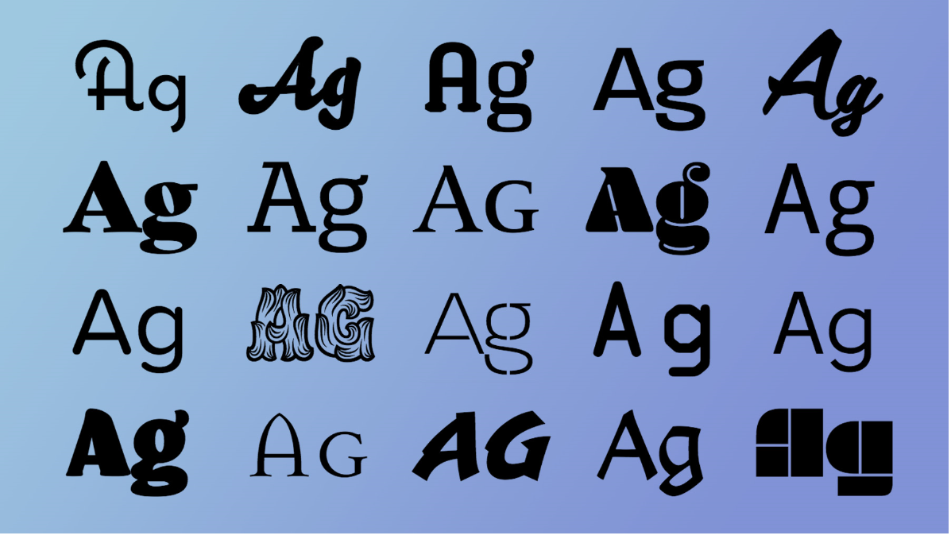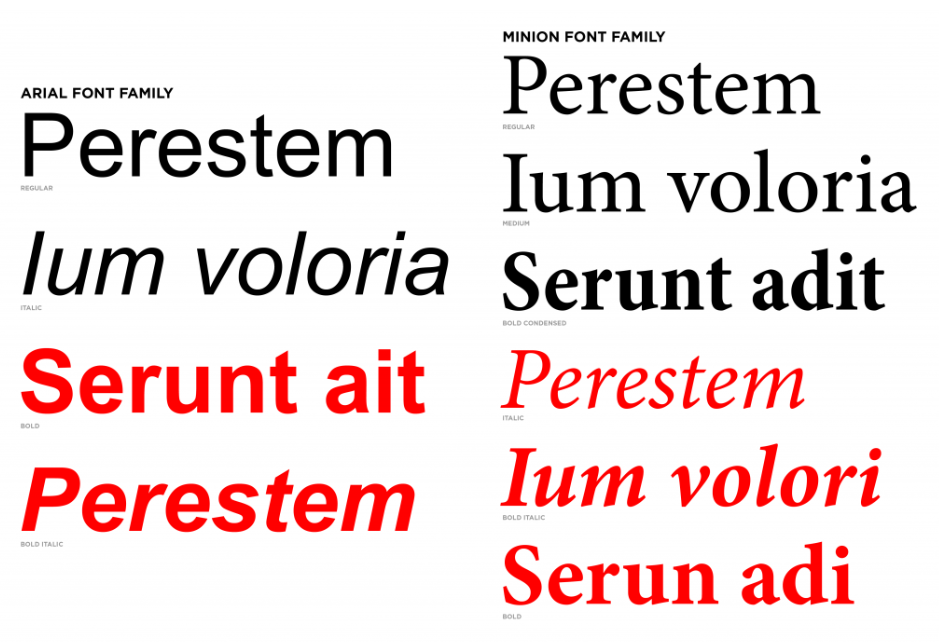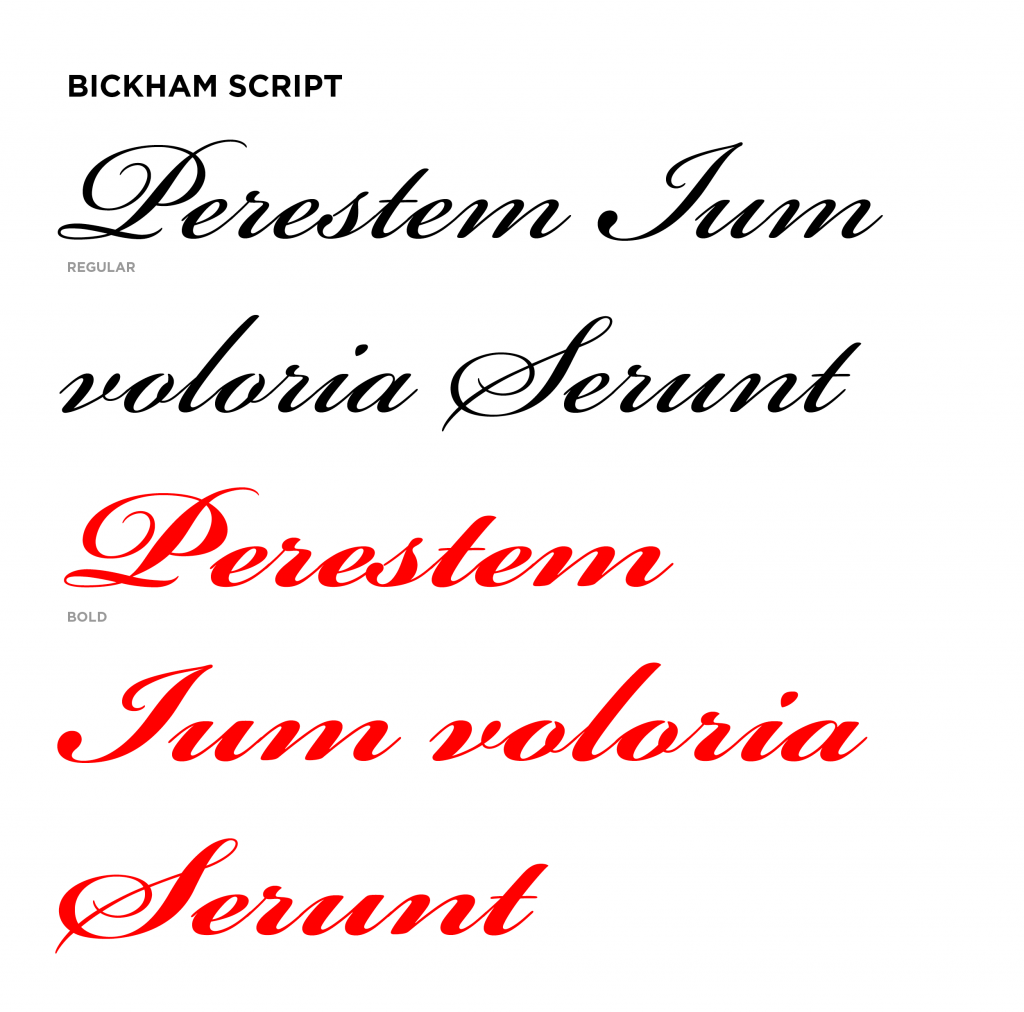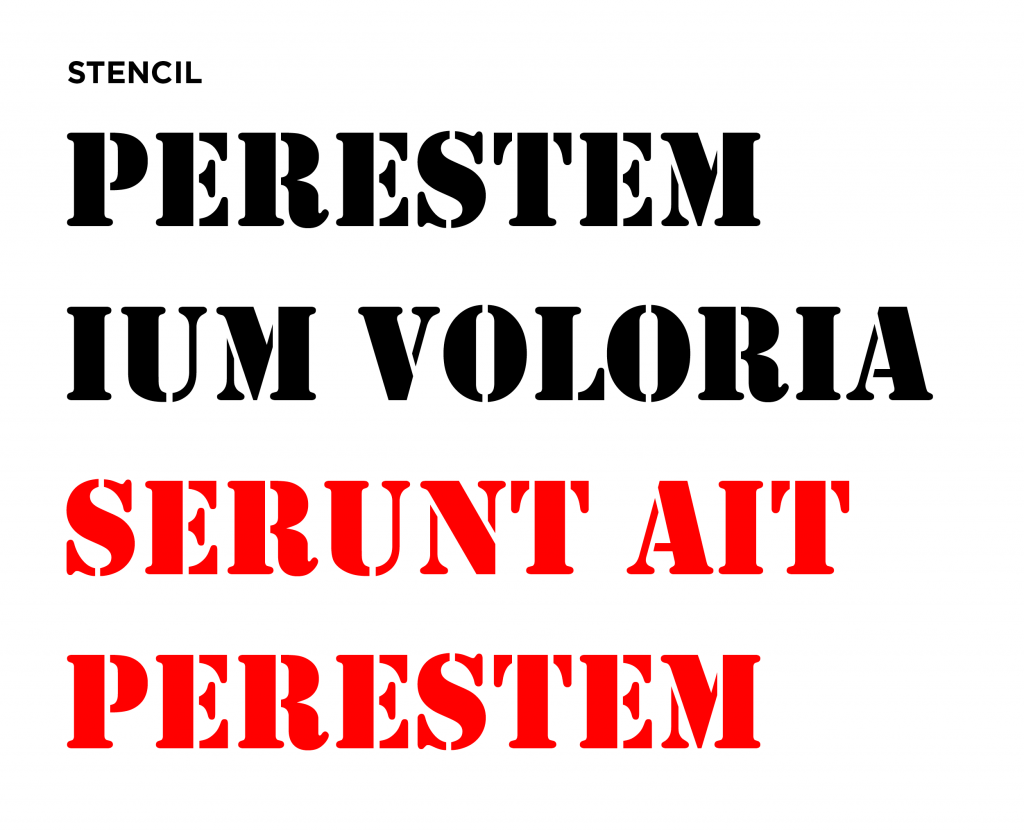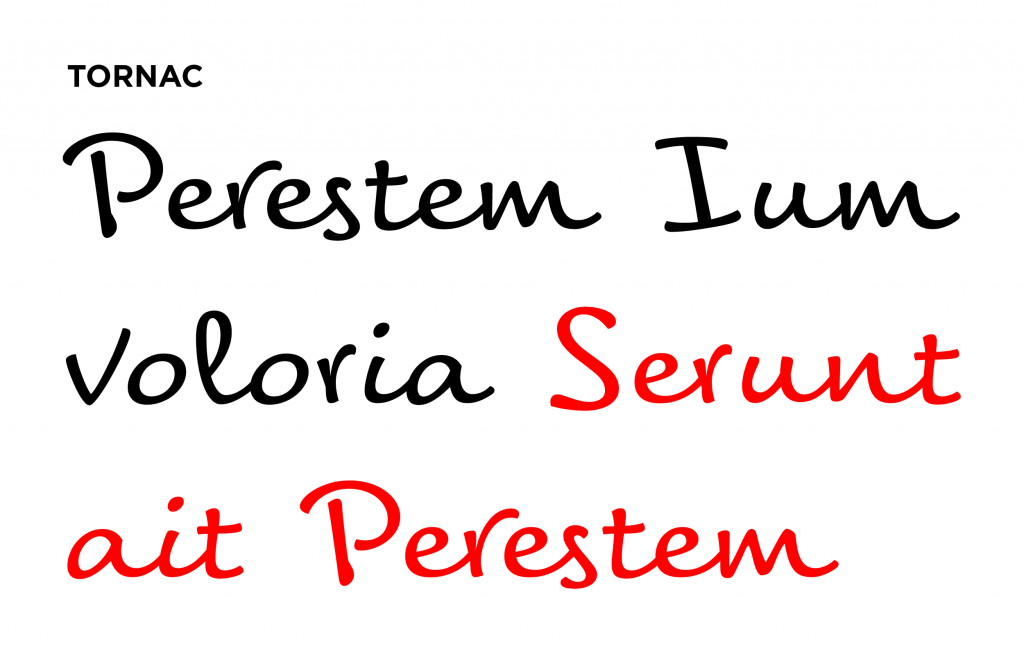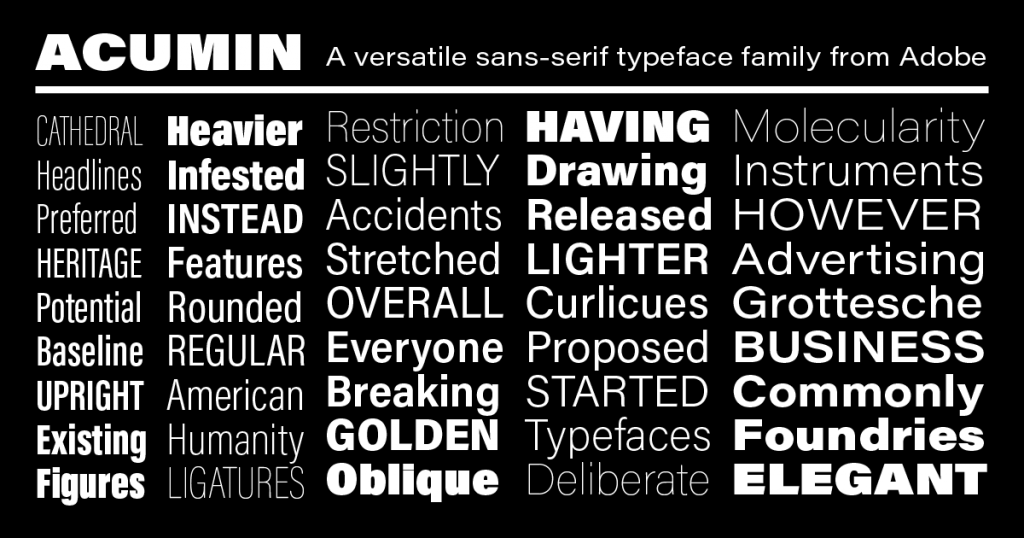
글꼴의 기능과 디자인에 적합한 글꼴 선택 방법
디자이너는 여러 종류의 디자인 의뢰를 받습니다. 예컨대 회사 세미나를 홍보하는 전단이나 친구의 결혼식 청첩장까지 다양합니다. 디자이너는 프로젝트가 최종적으로 어떻게 보여져야 하는지 알고 있습니다. 어떤 느낌을 전달해야 하는지도 알지만, 결과물은 어딘지 모르게 미흡합니다.
이와 비슷한 경험이 있다면 글꼴에 주목할 필요가 있습니다.
| 글꼴의 정의
워드 프로세서를 사용해 본 사람이라면 “글꼴”에 대한 기본적인 이해가 있을 것입니다. 그러나 의미 전달 측면에서 글꼴이 중요한 역할을 하는 디자인 프로젝트를 수행하는 경우 활자, 서체 및 글꼴의 차이점을 명확하게 파악하고 있어야 합니다.
• 활자는 현재 시각적인 문자를 통칭하는 일반적인 용어이지만, 본래는 글자를 만드는 데 사용된 나무 또는 금속 조각을 일컫는 말이었습니다.
• 타이포그래피는 인쇄된 텍스트의 스타일과 모양을 가리키는 디자인 용어입니다. 디자이너는 텍스트를 시각적으로 디자인하고 배열함으로써 타이포그래피를 전문적으로 다룰 수 있습니다.
• 서체(또는 글꼴 모음)는 글자 및 기호가 서로 비슷한 특징을 가지도록 디자인된 문자입니다. 예를 들어 타임즈(Times), 에어리얼(Arial) 및 미니언(Minion)은 모두 서체에 해당합니다.
• 글꼴은 서체의 특정 스타일을 가리킵니다. 에어리얼 블랙(Arial Black)은 에어리얼 서체 중 한 글꼴입니다. 미니언 프로 이탤릭체(Minion Pro Italic)는 미니언 글꼴 모음에 포함되어 있는 글꼴입니다.
“글꼴”이라는 용어는 서체 또는 글꼴 모음의 특정 스타일을 가리키는 말입니다. 에어리얼 블랙은 에어리얼 글꼴 모음의 한 글꼴이며, 미니언 프로 이탤릭체는 미니언 글꼴 모음의 한 글꼴입니다.
| 글꼴이 중요한 이유
독자가 정보를 읽고 이해하는 데 아무런 문제가 없다면 프로젝트에서 글꼴을 선택하는 일이 크게 중요하지 않다고 생각할 수 있습니다. 그러나 활자는 디자인에서 씌여진 메시지를 공유하는 것 이상의 역할을 합니다. 글꼴은 활자의 전체적인 느낌을 정의하고 견고한 브랜드 아이덴티티를 형성하는 데 큰 영향을 미칩니다.
브랜드 마케팅 에이전시인 스팍수(Sparxoo)의 멀티미디어 아트 디렉터인 조쉬 배런(Josh Baron)은 “활자 선택은 매우 중요한데, 브랜드의 경우 타이포그래피는 아이덴티티와 관련된 다른 모든 요소만큼이나 중요하며, 타이포그래피는 해당 브랜드의 메시지를 담는 그릇이라 할 수 있다”고 말합니다.
| 적합한 글꼴을 선택하는 방법
몇 가지 용어를 살펴보겠습니다. 글꼴은 기본적으로 세리프(serif)와 산세리프(sans serif)의 2가지 스타일로 나뉩니다. 세리프는 글자의 획 끝에 작은 삐침이 있는 글꼴입니다.
• 칼리브리(Calibri)는 산세리프 글꼴입니다.
• 캠브리아(Cambria)는 세리프 글꼴입니다.
최근의 디자인에서는 본문 글꼴로 세리프나 산세리프 서체가 모두 사용되고 있습니다. 글꼴을 선택할 때는 명확하고 가독성이 높은 단순한 형태의 글꼴을 선택하는 것이 좋습니다. 글꼴을 결정하기 전에 컴퓨터에서 한 발짝 물러나 가독성을 테스트합니다. 인쇄물 형태로 만들어야 하는 경우 선택하려는 글꼴의 샘플을 인쇄하여 의도한 글꼴이 실제 종이에서는 어떻게 보이는지 확인합니다. 글꼴에 따라 컴퓨터 화면보다 실제 크기의 포스터에서 훨씬 더 잘 읽히는 경우가 있습니다.
어도비 서체(Adobe Type) 팀의 선임 관리자인 댄 라티건(Dan Rhatigan)은 “테스트를 통해 직접 확인하는 것이 중요”하다며 “이름이 마음에 든다거나 흥미롭다는 이유만으로 서체를 고르는 것은 금물이며, 몇 개의 서체를 정해 각 서체가 디자인과 조화를 이루는지 살펴보고 비교해야 한다”고 조언합니다.
다양한 글꼴을 실험해 보는 것을 주저하지 마십시오. 특히 초보 디자이너라면 더욱 그렇습니다. 페이지에서 직접 보기 전까지는 글꼴이 디자인에 어울리는지 판단하기 어려운 경우도 있습니다.
| 가독성 향상을 위한 글꼴수 제한
일관된 디자인 작업을 할 때 염두에 두어야 하는 가장 중요한 사항 중 하나는 프로젝트에 사용할 글꼴의 개수를 2~3개로 제한하는 것입니다. 디자인 섹션마다 너무 많은 글꼴을 사용할 경우 독자의 집중을 방해하고 혼란을 줄 수 있습니다.
다른 디자인 요소와 마찬가지로 글꼴은 대비 및 반복과 같은 기본 원칙을 바탕으로 선택해야 합니다. 여러 글꼴을 사용할 계획이라면 각 글꼴이 사용되는 텍스트를 명확하게 구분할 수 있을 정도로 뚜렷하면서도 시각적으로 조화로운 글꼴을 찾아야 합니다.
상호 보완적이고 디자인의 다양성까지 얻을 수 있는 글꼴을 찾는 데 가장 효과적인 방법은 하나의 글꼴 모음에 속해 있는 글꼴을 사용하는 것입니다. 볼드(Bold), 이탤릭(Italic), 라이트(Light), 미디엄(Medium) 및 블랙(Black)과 같은 옵션이 함께 제공되는 서체를 선택합니다. 동일한 글꼴 모음에 속해 있는 여러 글꼴들은 서로 조화를 이룰 뿐만 아니라 텍스트를 구분하고 프로젝트에 집중할 수 있도록 돕습니다.
• 예를 들어 알레그레이야(Alegreya) 글꼴은 보통, 볼드체 및 이보다 굵은 블랙 옵션을 제공합니다.
| 디자인을 돋보이게 하는 방법
산세리프(Sans serif)와 세리프(Serif) 글꼴은 본문에 사용하기 적합하지만, 좀더 시선을 끄는 디자인을 위해서는 조금 더 매력적인 디스플레이 또는 머리글 글꼴을 사용하는 것이 좋습니다.
댄은 “머리글의 주된 기능은 몇 개의 단어만으로 독자의 주의를 집중시키는 것이므로 머리글에 보다 다양한 글꼴을 적용할 수 있는데, 너무 크거나 쉽게 알아볼 수 없는 작은 서체를 배제하는 것이 주의 집중을 위한 한결 쉬운 방법”이라고 조언합니다.
• 비컴 스크립트(Bickham Script)와 같은 스크립트체 글꼴은 우아하거나 예술적인 표현이 필요한 디자인에 이상적입니다.
머리글에 사용된 글꼴은 프로젝트의 성격을 드러낼 수 있습니다. 예를 들어 위의 스크립트체 글꼴은 우아한 느낌을 줄 수 있습니다.
• 스텐실(Stencil)과 같은 굵은 장식체 글꼴은 디자인에서 특정 아이디어를 부각시키고 중요한 디자인 요소를 강조하는 데 유용합니다.
스텐실과 같은 많은 장식체 글꼴은 내용을 강하게 부각시키고 메시지에 시선을 집중시킬 수 있습니다.
• 토르낙(Tornac)과 같은 손글씨체 글꼴은 이름에서 알 수 있듯이 손글씨를 흉내 낸 글꼴이므로 복고풍이나 친근함을 표현해야 하는 디자인에 이상적입니다.
손글씨를 흉내 낸 토르낙과 같은 글꼴은 친근함을 줄 수 있습니다.
| 원하는 글꼴을 자유롭게 이용하기 위한 팁
어떤 글꼴을 선택해야 할지 망설여지는 경우 다양한 글꼴 스타일을 제공하는 애큐민(Acumin)과 같은 서체부터 시작해 보십시오.
적합한 글꼴을 단번에 찾기 어렵다면 대부분의 디자인 테마에 잘 어울리는 것으로 입증된 서체를 사용해 보시기 바랍니다. 산세리프 서체인 애큐민에는 깔끔하고 가독성이 높은 다양한 글꼴 스타일이 포함되어 있으며, 세리프 글꼴 모음인 잉게보르크(Ingeborg)는 시각적으로 돋보일 수 있는 다양한 옵션을 제공합니다. 세리프 글꼴과 산세리프 글꼴을 함께 사용하고자 하는 경우 스콜라(Skolar)와 스콜라 산스(Skolar Sans)를 사용해 보십시오. 두 글꼴은 상호 보완을 고려하여 디자인되어 서로 조화를 이룹니다.
프로젝트에 사용되는 텍스트는 프로젝트 결과에 긍정적인 영향을 미치는 필수 요소입니다. 완벽한 글꼴은 사람들의 시선을 사로잡고 메시지를 분명하게 전달할 수 있으며 나아가 브랜드를 대표할 수도 있습니다. 즐겨 사용하는 글꼴 목록을 살펴보고 이를 디자인 앱에 동기화하여 사용해 보십시오.